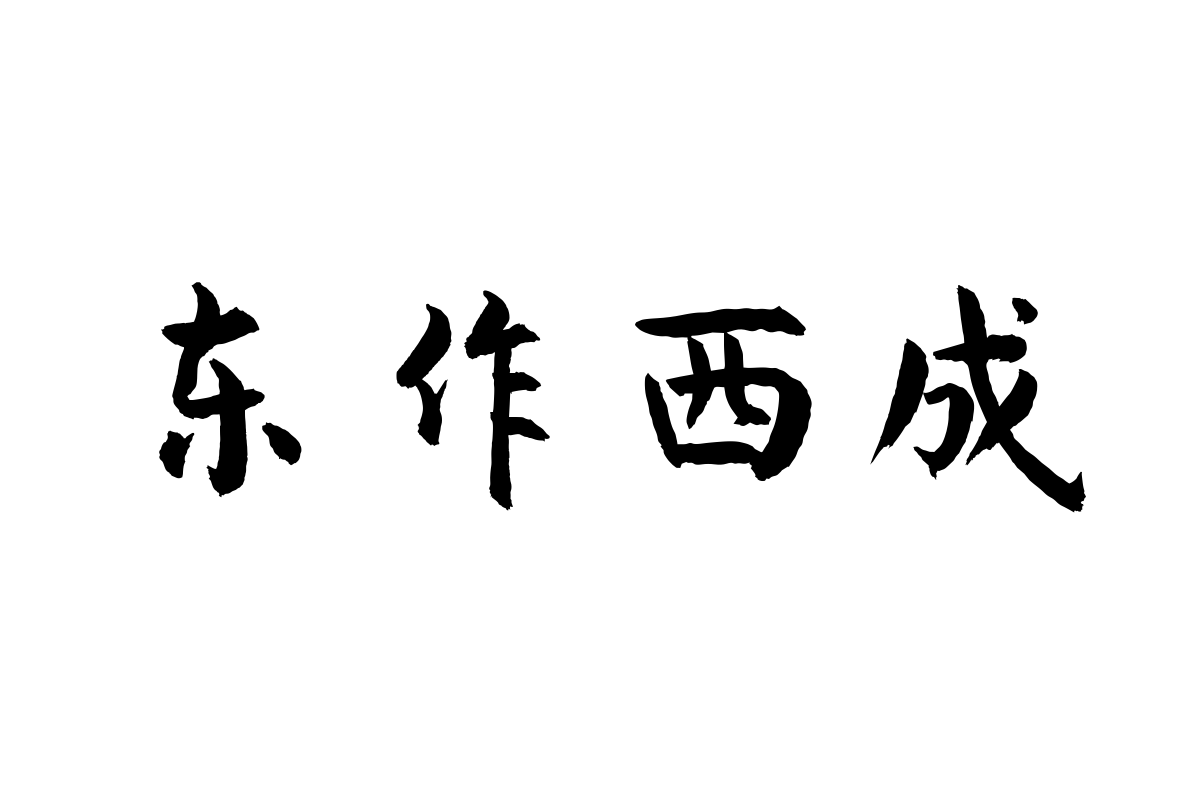
汉仪李国兴行楷字体是一款具有现代感和艺术性的中文字体,其特点是笔画流畅、结构紧凑、字形美观。这款字体适用于各种设计场景,如广告、包装、书籍等,能够为作品增添独特的视觉风格。
汉仪李国兴行楷字体的特点如下:
1. 笔画流畅:这款字体的笔画线条流畅自然,没有过多的装饰性笔画,给人一种简洁、大方的感觉。
2. 结构紧凑:在保持笔画流畅的同时,汉仪李国兴行楷字体的结构紧凑,字形紧凑而不拥挤,适合用于需要展现文字美感的设计场景。
3. 字形美观:这款字体的字形优美,线条粗细适中,既有力度又有柔美,能够很好地展现出汉字的韵味。
4. 适用范围广泛:汉仪李国兴行楷字体适用于各种设计场景,无论是广告、包装还是书籍,都能够为其增添独特的视觉风格。
5. 易于使用:这款字体的字形规则,易于识别和使用,适合设计师进行快速设计。
总之,汉仪李国兴行楷字体是一款具有现代感和艺术性的中文字体,其笔画流畅、结构紧凑、字形美观等特点使其成为设计师们的首选字体之一。